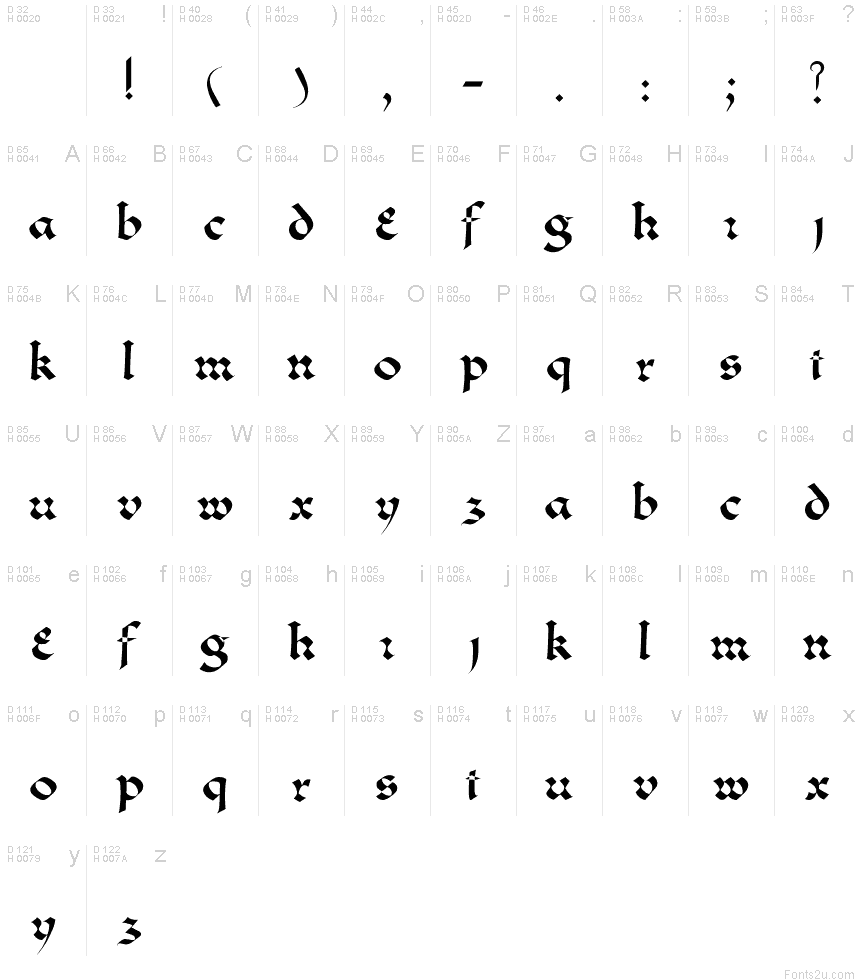
Lombardo-Beneve, darmowy średniowieczny krój gotycki od Atech Software, wykorzystuje masywną, gotycką bryłę oraz wyraziste, rombowe detale, by nawiązywać do pisma ręcznego z dawnych manuskryptów, unikając przy tym nadmiernej ozdobności. Rytm pisma pozostaje zwarty i surowy, a kanciaste przełamania i klinowate zwieńczenia nadają mu solidny, rzeźbiarski charakter na tle całego alfabetu.
Świetnie sprawdzi się na szyldach pubów, w tytułach gier fantasy, na plakatach jarmarków historycznych, gadżetach muzycznych oraz w nagłówkach rozdziałów, gdzie potrzebny jest historyczny klimat o konkretnej sile przebicia. Dzięki zdyscyplinowanym i powtarzalnym formom dekoracyjnym, Lombardo-Beneve stanowi doskonałe oparcie dla krótkich nagłówków i logotypów, nie tracąc czytelności na rzecz przesadnej kaligrafii.